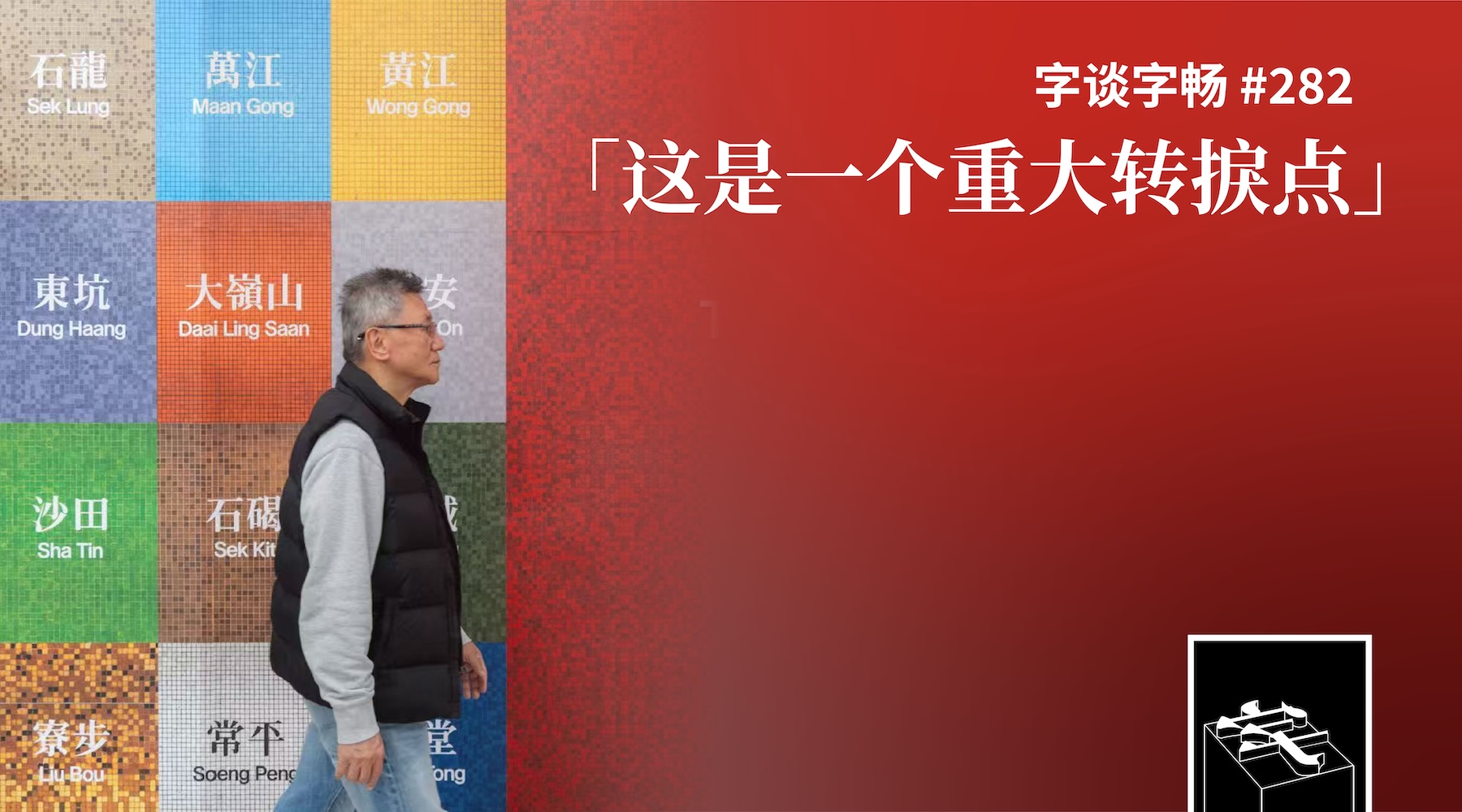
TypeChat #282
柯炽坚先生的新作「铁宋 Plus」面世,在铁宋家族的风格之上,扩大字符集、优化排版特性、落地方言用字支持并拆分简体与繁体封装,也为后续的家族扩展定下新的基础。
本期节目,我们有幸请来主创设计师柯先生,以及团队核心成员梁佳、厉致谦,为大家介绍「铁宋 Plus」及其背后的故事。